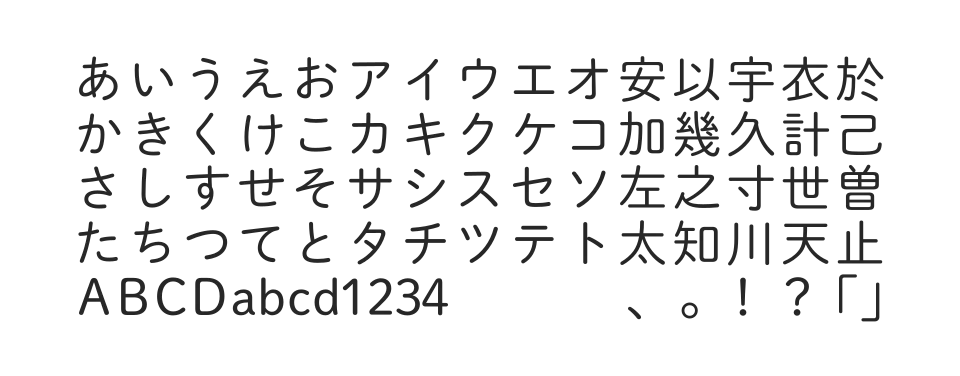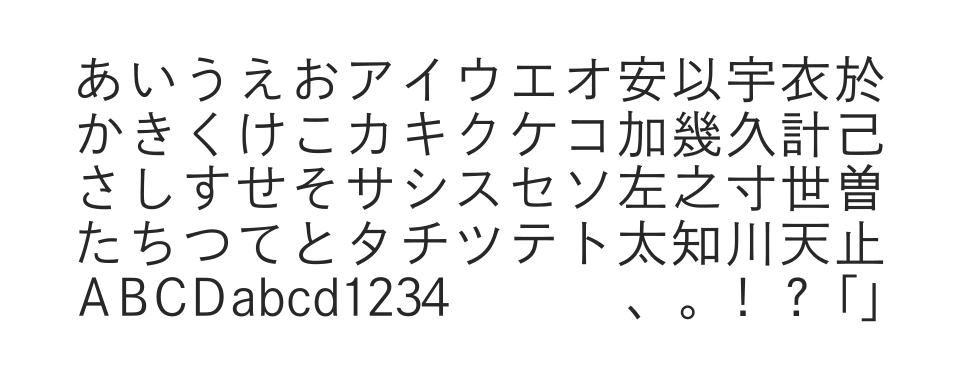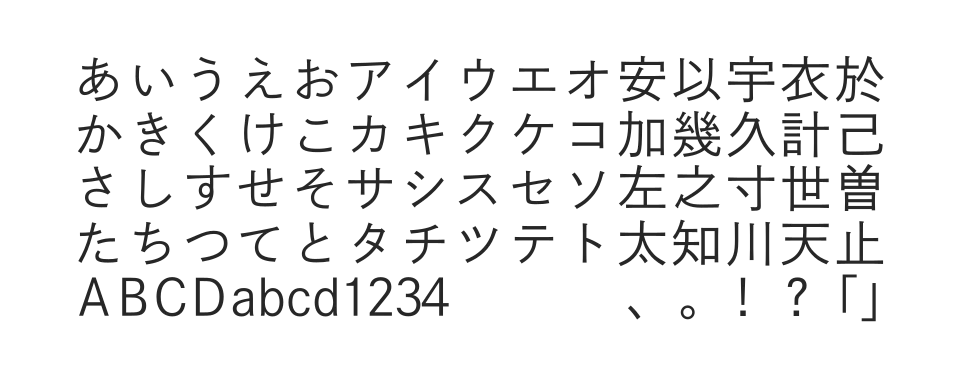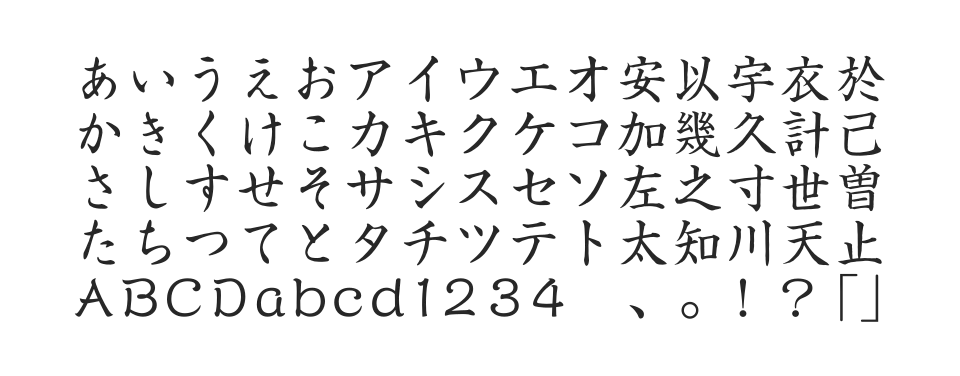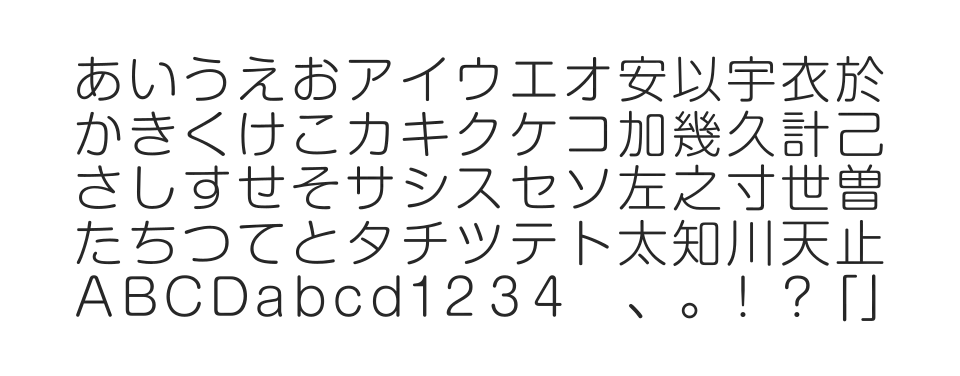
モダンなゴシック体として人気の高い「新ゴ」をもとに誕生した丸ゴシック体。明るく洗練された雰囲気に加えて、丸味のあるエッジがもたらすやさしいイメージと親しみやすさが特徴です。
筆文字の力強さや重厚感を大切にしながら、漢字・かなの大きさを揃えることで字並びの美しさと使いやすさを追求した楷書体。人間味を感じさせる丁寧な筆使いが特徴です。
秀英明朝の骨格を活かしたクラシックな印象のゴシック体。フトコロの締まったかなは本文を組んでも見やすく、特に縦組みで効果を発揮する落ち着きのある書体です。
秀英体の伝統的なゴシック体。明るい表情でオーソドックスに幅広く使える書体。秀英明朝とマッチするデザインで、大ぶりで手書き字形にも近いかなが特徴です。
大日本印刷が100年以上にわたり開発してきた伝統ある書体。クラシックな印象を持つ丸ゴシック体で、やわらかな表情の中にも説得力を感じさせる書体。本文用としての適性も十分に備えています。
モリサワの定番ゴシック体。活字書体のデザインを忠実に継承し、視認性に優れた力強いゴシック体です。用途を選ばず広範囲に使用可能。
秀英明朝のPr5版。Adobe-Japan1-5準拠でより多くの文字に対応。幅広い用途に使える明朝体です。
秀英明朝のPr6版。Adobe-Japan1-6準拠で豊富な文字数を収録。専門的な用途にも対応した明朝体です。